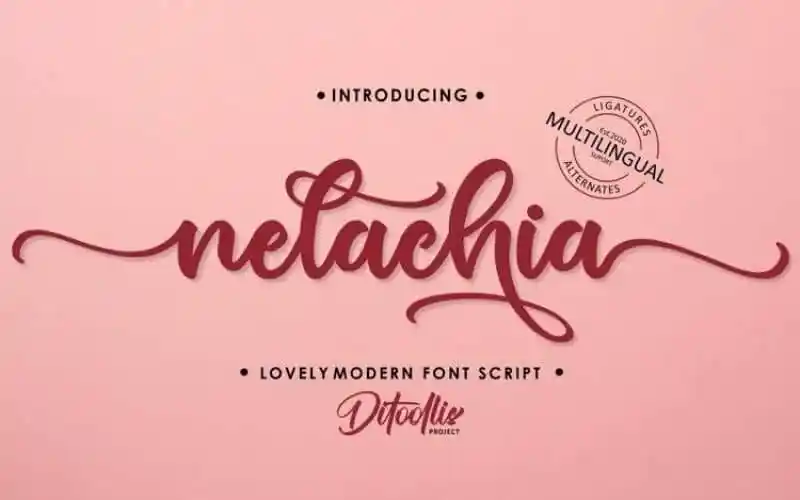
A Nelachia Calligraphy Font é uma escolha perfeita para quem deseja dar um toque elegante a seus projetos. Criada pelo designer DitoollisProject, esta fonte tipográfica moderna oferece detalhes exóticos e alternativas estilizadas para textura. Além disso, inicia e finaliza cada letra com uma espiral do coração, garantindo um toque romântico e único. Ideal tanto para cards de negócios quanto para logotipos, capas, quadrinhos ou convites especiais, a Nelachia Calligraphy Font é perfeita para quem deseja transmitir elegância em qualquer projeto. Com seu design sofisticado e suas nuances distintivas, esta fonte trará um toque personalizado à sua produção gráfica.